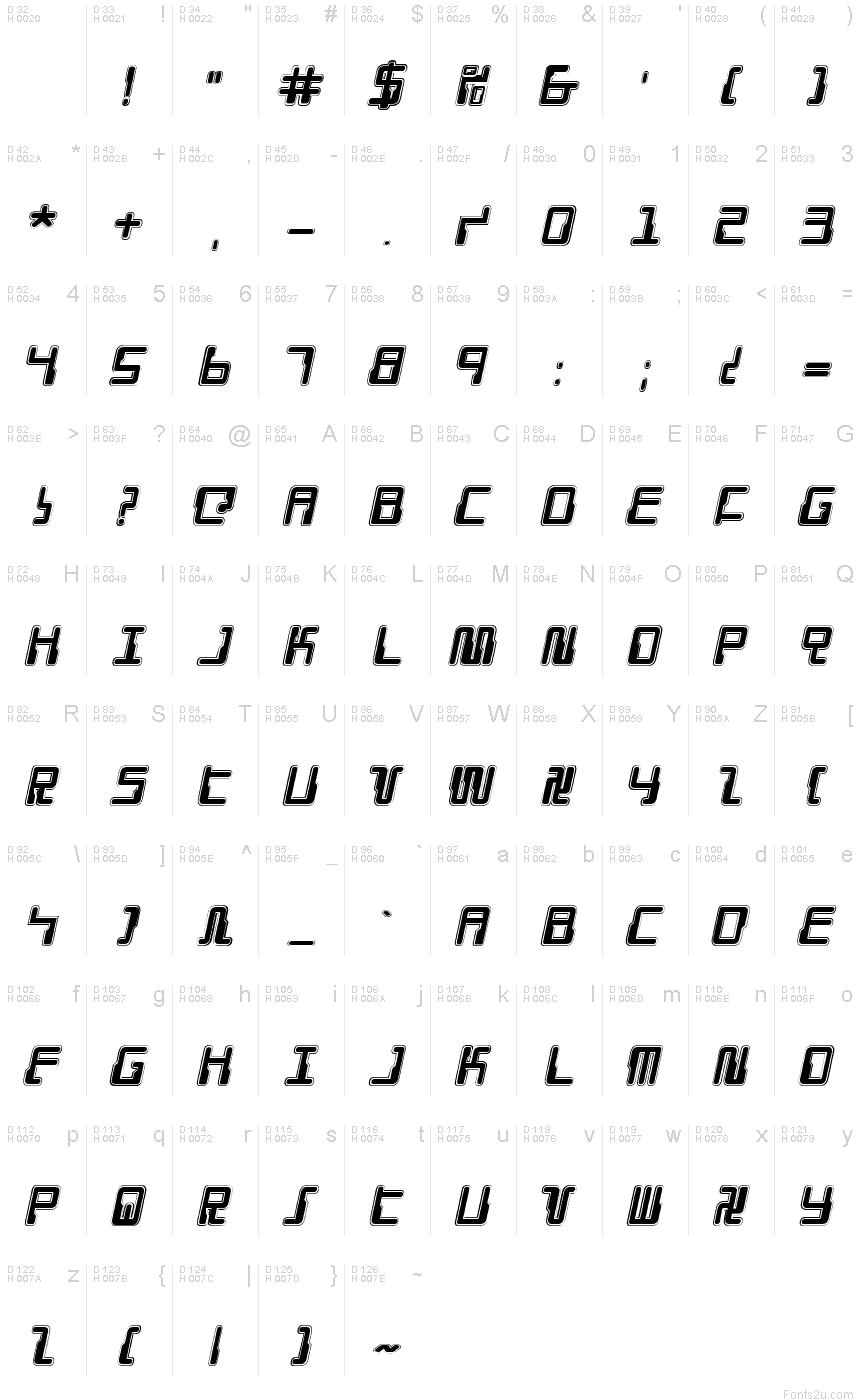
Droid Lover Pro Italic di Iconian Fonts è un font display futuristico gratuito, caratterizzato da maiuscole dagli angoli netti e una decisa inclinazione in avanti. Le lettere sembrano modellate sulla carrozzeria di un veicolo sci-fi, unendo angoli smussati a un trattamento a contorni sovrapposti che dona al font una presenza massiccia e meccanica, senza perdere quell'estetica techno raffinata tipica degli anni 2000.
È la scelta ideale ovunque serva un carattere sintetico e ad alta velocità: loghi di videogiochi, grafiche per musica elettronica, titoli di poster, opening di film e monogrammi taglienti valorizzano al meglio questo font gratuito. Grazie alle maiuscole ampie, inclinate e visibilmente incorniciate, il font rende particolarmente bene nelle parole brevi e nei brand mark, dove la struttura profilata cattura subito l'attenzione.